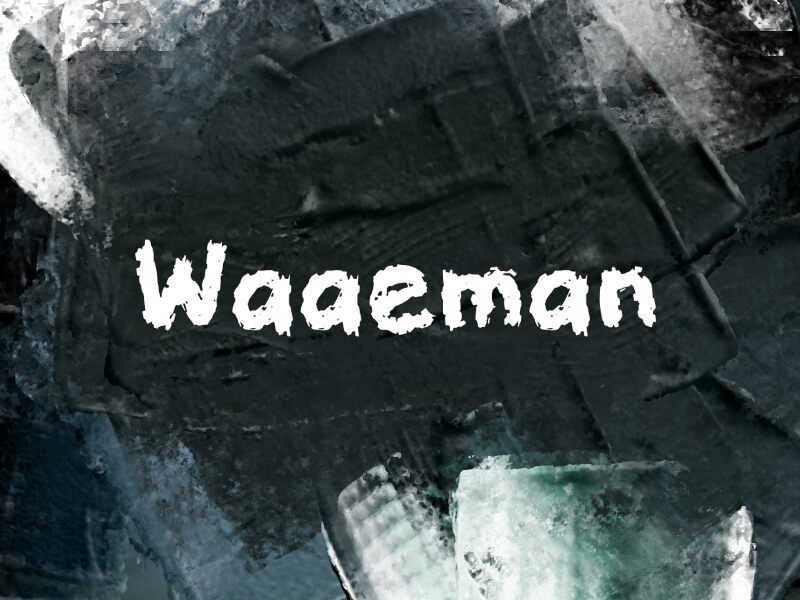
Waaeman من Wep هو خط فرشاة مجاني يتميز بملمس كثيف يشبه الفرشاة الجافة وحواف خشنة تمنح الحروف طابعاً حيوياً. بدلاً من الخطوط الناعمة، تبدو الأشكال وكأنها محفورة ومشبعة بحبر متقطع، مما يمنح الخط مظهراً يدوياً خشناً بدلاً من الطابع التقليدي المصقول.
هذا الملمس مثالي للمنشورات الموسيقية، وملصقات الرعب، وتصاميم ملابس الشارع، وعناوين الألعاب، واللافتات على وسائل التواصل الاجتماعي التي تتطلب طابعاً خاماً وجريئاً. كما أنه ممتاز للاستخدام في العبارات القصيرة على العبوات وهويات الفعاليات، حيث يوفر تأثير الفرشاة البالية أسلوباً جاهزاً دون الحاجة إلى مؤثرات إضافية.
Waaeman
عرض ونموذج مرئي لخط Waaeman